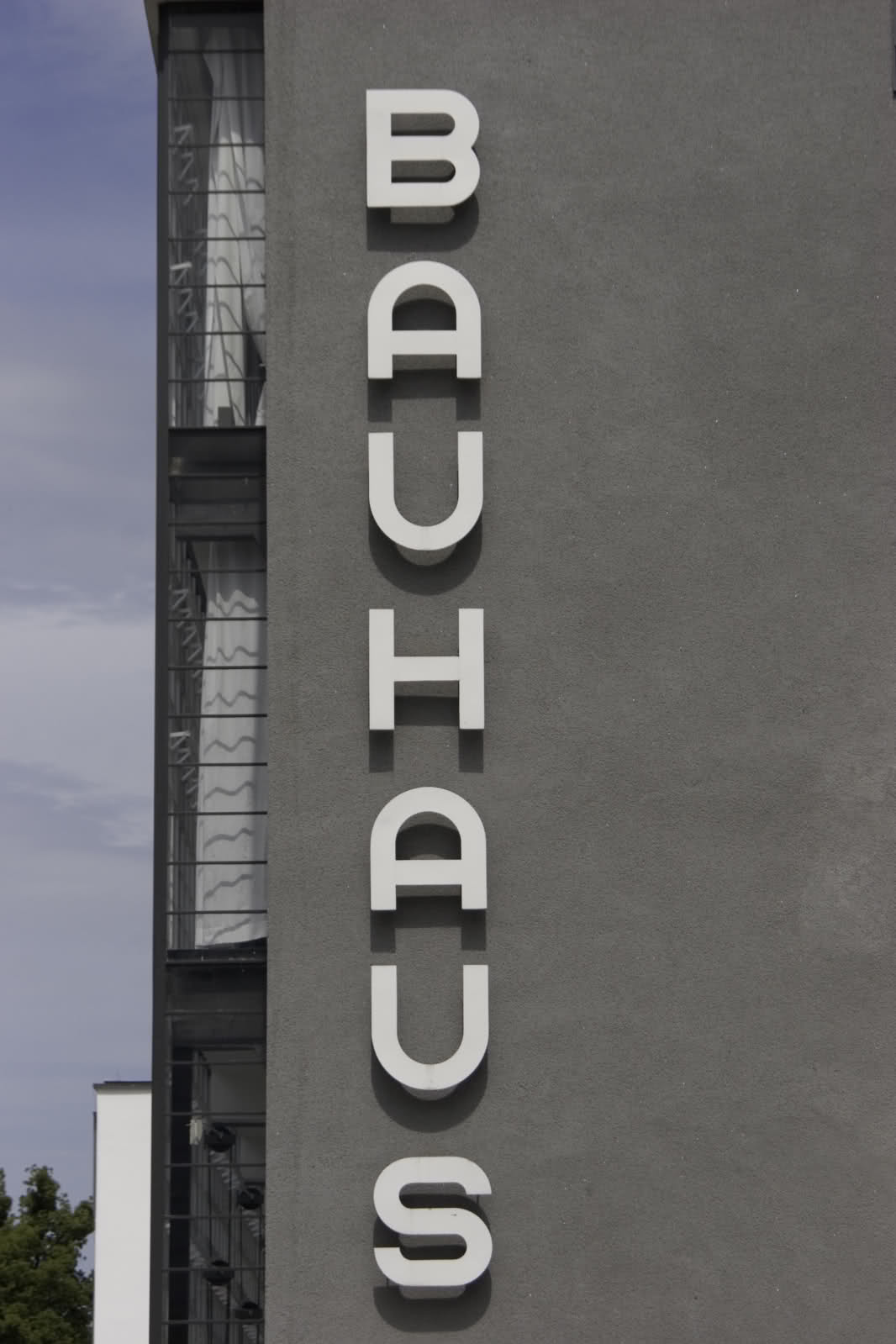
ich suche die BAUHAUS-Schrift, die in Dessau an der Schule angebracht ist... wenn möglich, genau die und wenn möglich für lau... wäre total genial!
also ich benötige die Schrift für ein Schriftplakat (Studium) und da dieses Jahr ja Bauhaus-Jubiläum ist, ich schon in Dessau, Weimar und Berlin war, suche ich nunmal nach der perfekten Bayer-Schrift... hab mir in Berlin zwar so meine Skizzen gemacht, müsste dann aber alles selbst bauen und das ist natürlich auch in den seltensten Fällen perfekt... :/
auch andere Zeichen.... "Dessau" ebenso und dann auch noch ein paar weitere Wörter und auch Zahlen... :/
dann muss ich passen, DESSAU hätte ich noch aber mehr nicht, du bist aber jung und hast zeit, du schaffst das :rockon:
am besten sich ein raster bauen und mit einer starken linie arbeiten die man dann in ein objekt (umrisse) umwandelt, so kompliziert ist das nicht.
(notiz an mich: irgendwann den »bauhaus dessau« font machen)
da es für das Fach Kalligrafie und somit analog, per Hand auf ein großes Brett sein soll, mach ich mir so meinen Grundstock am PC und meine Schablonen können ja eh noch variieren ;)
...und vielleicht hab ich ja ein wenig Interesse aufs Bauhaus geweckt...?!
bla.....Kalligrafie muss nicht die typische "Schönschreib-Kunst" sein...! Es geht einfach um ein kulturelles Schrift-Plakat, welches eben per Hand entstehen soll....die und so schneide ich mir halt für jeden Buchstaben eine Papierschablone zurecht und setzte die dann :-P